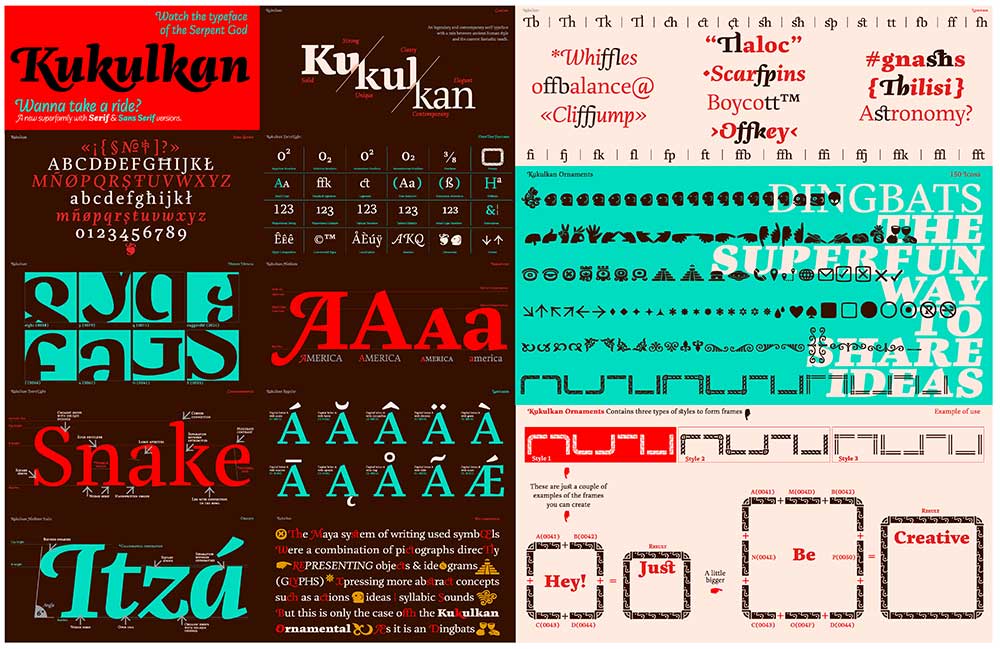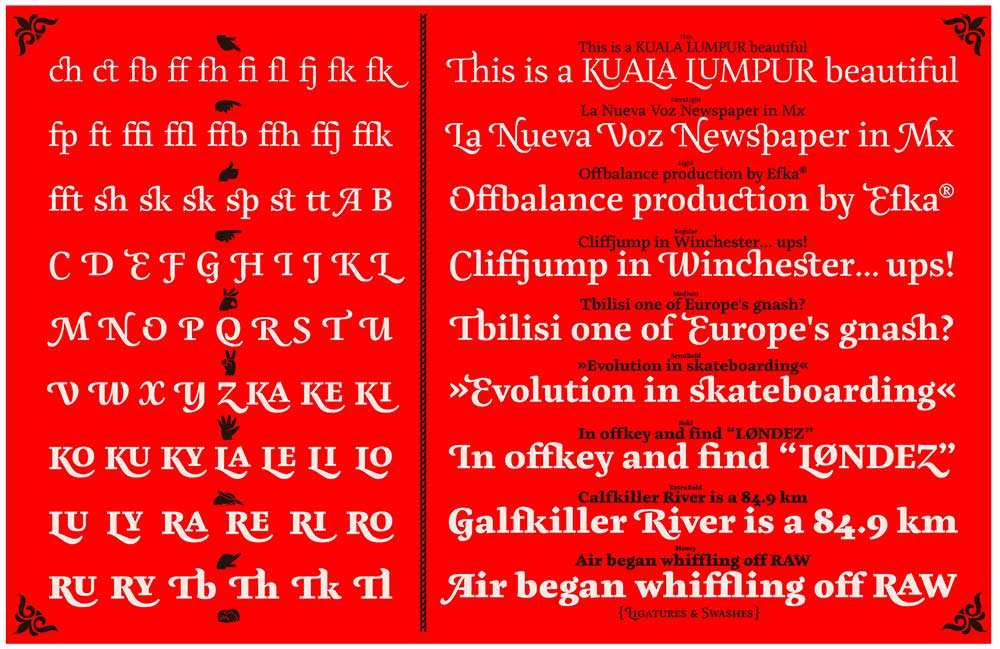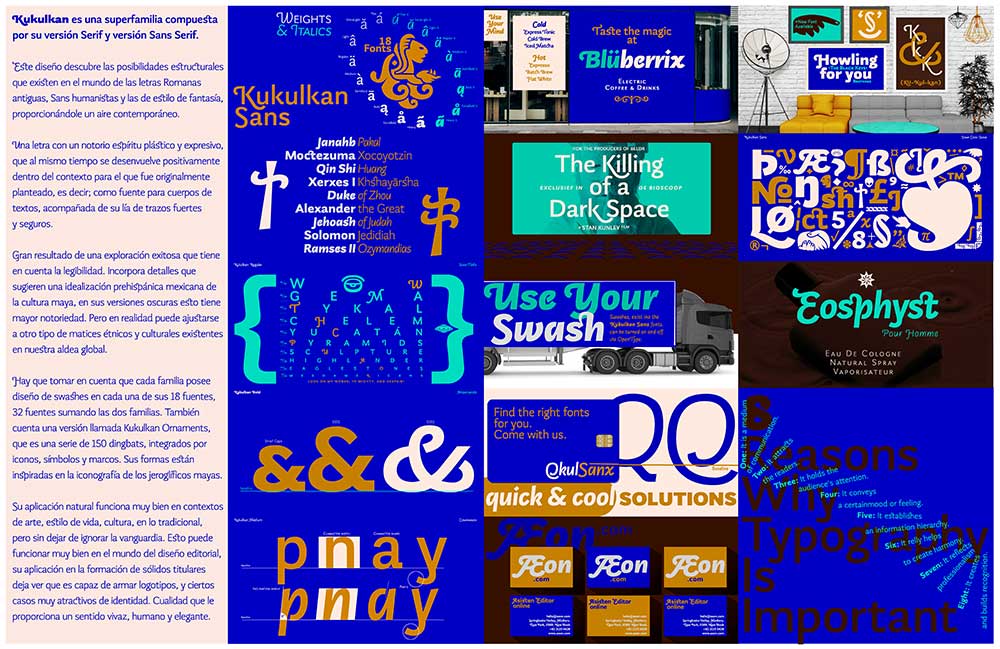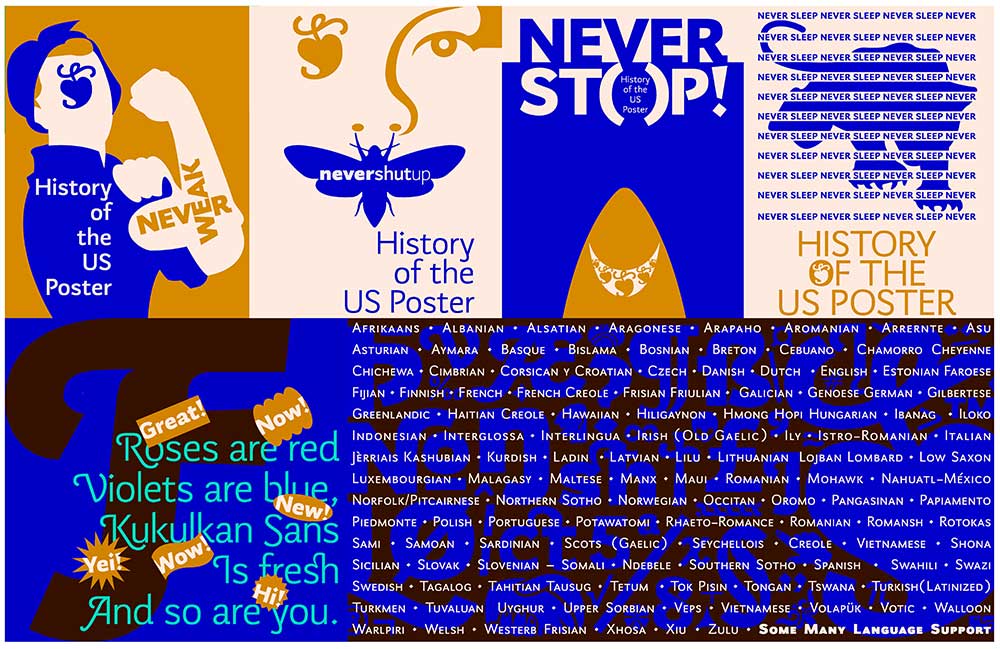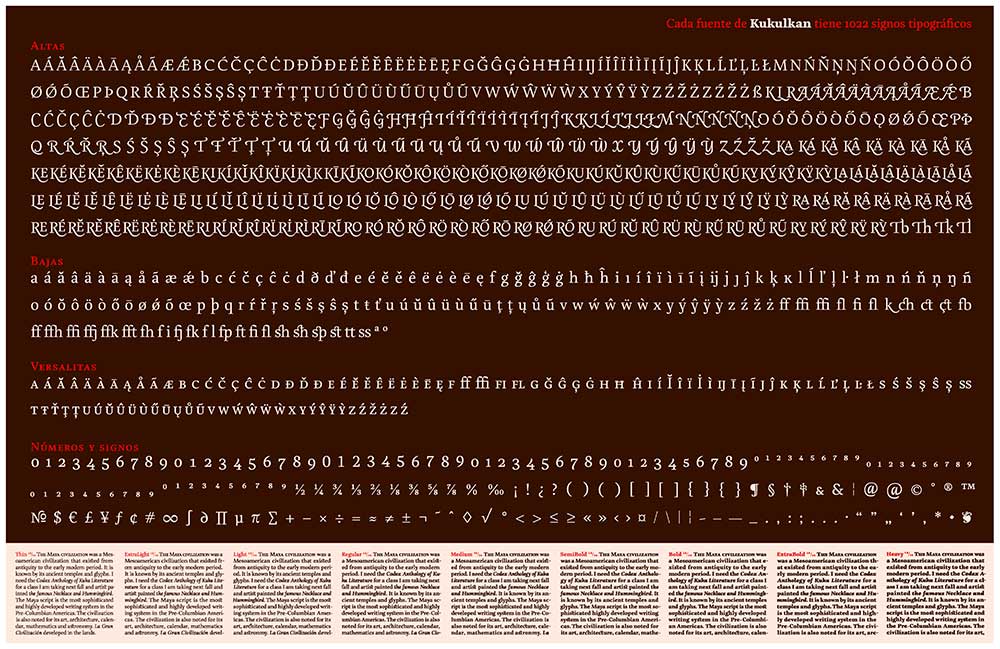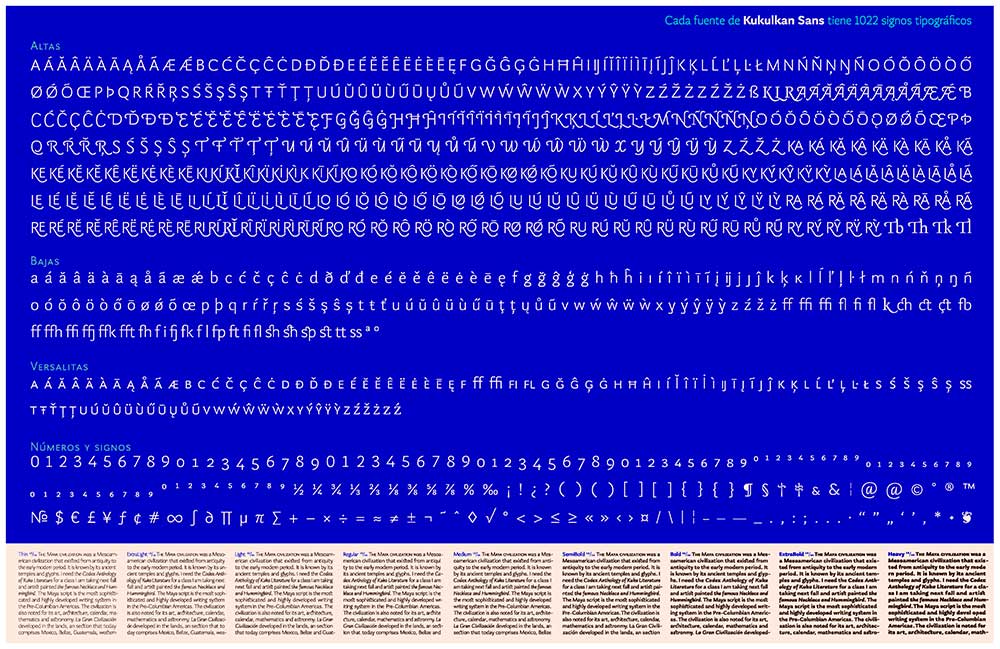
Superfamilia tipográfica compuesta por sus versiones serif y sans serif. Este diseño descubre las posibilidades estructurales que existen en las letras romanas antiguas, sanshumanistas y las de estilo de fantasía. Tiene un notorio espíritu plástico y expresivo, que al mismo tiempo se desenvuelve positivamente dentro del contexto para el que fue originalmente creada: fuente para textos.